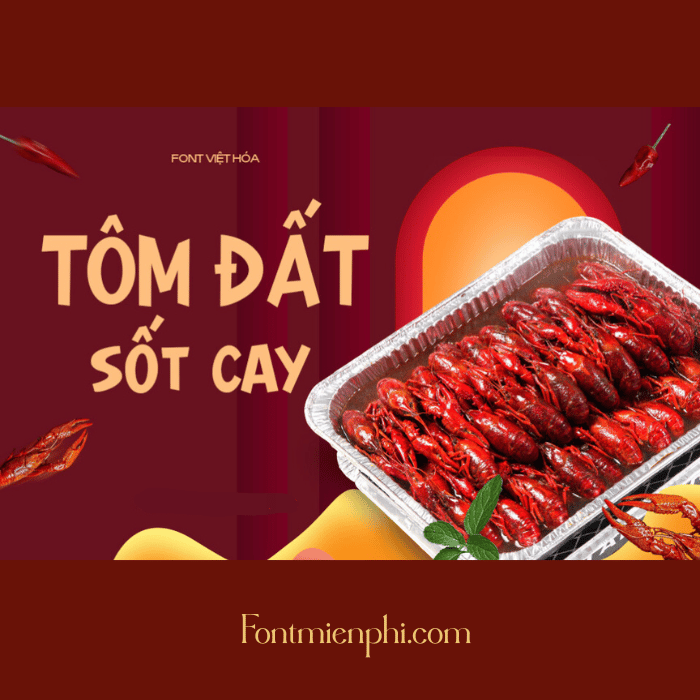
Font Việt hóa 1FTV VIP Komika – Phong Cách Độc Đáo Cho Thiết Kế
Font 1FTV VIP Komika là bộ font Việt hóa chất lượng cao, mang phong cách truyện tranh (comic) sống động, phù hợp cho thiết kế poster, logo, tiêu đề hay nội dung sáng tạo. Với nét chữ đậm, góc cạnh và đường nét mềm mại, Komika tạo điểm nhấn ấn tượng, giúp sản phẩm thiết kế của bạn trở nên nổi bật.
Đặc điểm nổi bật Font Việt hóa 1FTV VIP Komika :
✔ Hỗ trợ tiếng Việt đầy đủ – Tương thích với mọi phần mềm thiết kế.
✔ Đa dạng kiểu chữ – Phù hợp với nhiều phong cách từ cá tính đến hài hước.